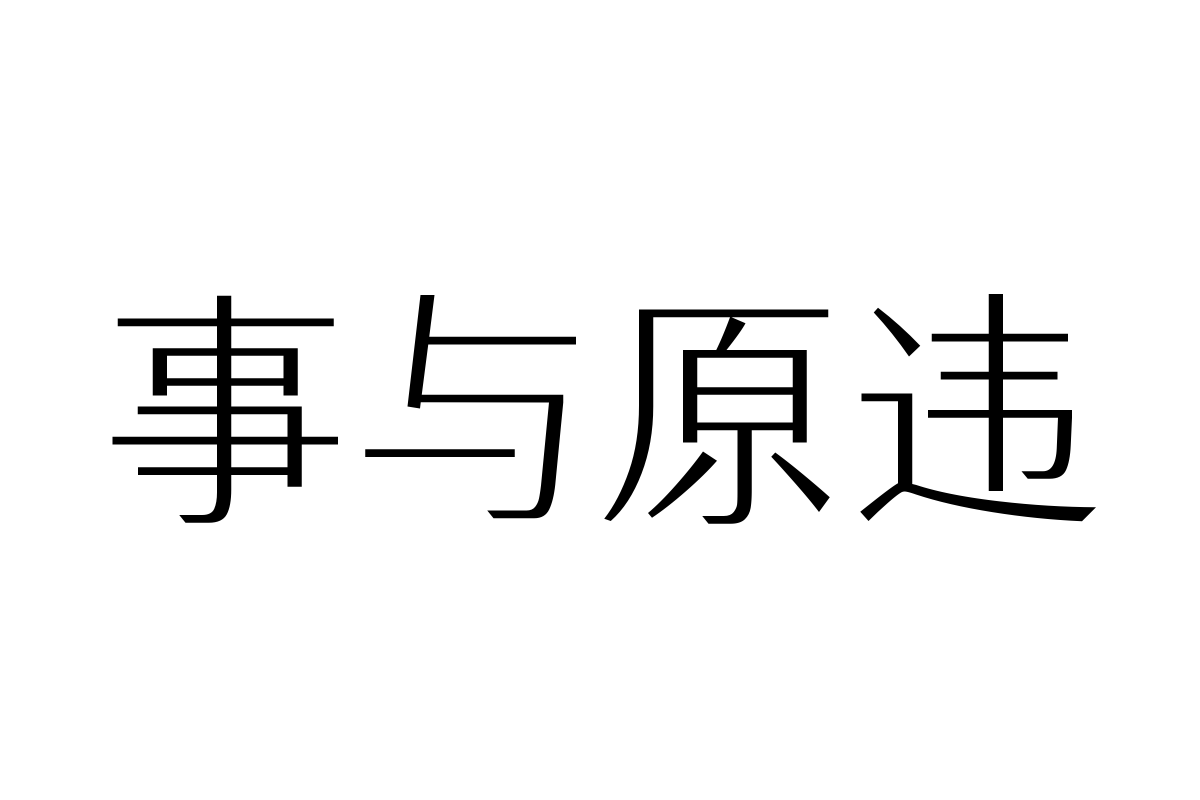
三极汉林简体是一种中文字体,由北京汉仪科印电子技术有限公司开发。该字体具有简洁、易读的特点,适用于各种商业和办公环境。
三极汉林简体的主要特点如下:
1. 笔画清晰:该字体的笔画线条流畅,易于阅读,适合用于需要清晰显示的文字。
2. 易读性高:由于笔画线条流畅,三极汉林简体的文字具有较高的易读性,适合用于各种商业和办公环境。
3. 适用范围广:三极汉林简体适用于各种类型的文字,如标题、正文、广告等,具有较强的通用性。
4. 兼容性好:三极汉林简体具有良好的兼容性,可以与其他字体混合使用,提高整体设计效果。
5. 可扩展性强:三极汉林简体支持多种字号和字形设置,可以根据设计需求进行调整,满足不同应用场景的需求。
总之,三极汉林简体是一种简洁、易读、通用性强的中文字体,适用于各种商业和办公环境。